손으로 적시는 디자인 감성, 캘리그라퍼(Calligrapher).2
아날로그 감성의 매개체, 캘리그래피. 1부에서 만난 세 명의 작가를 통해 캘리그래피의 예술성과 디자인적 발전 가능성을 살펴볼 수 있었다. 이번 2부에서는 두 명의 작가 이야기를 더 들어본다. KBS 방송타이틀로 잘 알려진 KBS아트비전 그래픽 디자이너 김성태, 북디자이너이자 캘리그래퍼인 이산캘리그래피 대표 이산 작가이다.
Q1. 캘리그리피 전문가로써 자신의 첫 작품이 궁금합니다.
저는 캘리그래퍼이기 전에 대한민국미술대전 초대작가로서 서예가란 표현에 더 익숙한 작가입니다. KBS에 입사하고 방송타이틀을 쓰면서 캘리그래퍼란 칭호가 붙기 시작한 것 같아요. KBS 입사 후 첫 방송타이틀을 만든 것이 “TV소설 찔레꽃”입니다. 70~80년대의 암울했던 시절을 그린 드라마인데, 우리 어머니 세대의 역경과 어려운 환경 등을 작품에 표현하려고 노력했죠. 캘리그래피 작업으로는 이 작품이 처음이 아닐까 합니다.
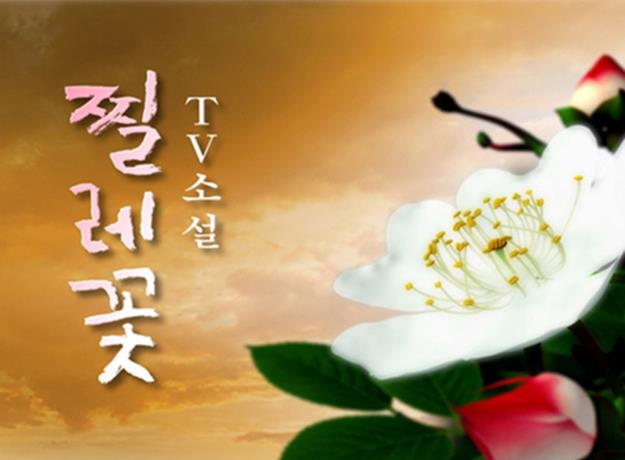
Q2. 지금까지 활동하면서 자신의 대표작 3점을 뽑는다면?
3점만 꼽기에는 조금 아쉽지만, 굳이 뽑아보자면 예전에 아침 프로로 방송된 “생방송 세상의 아침”과 최근의 “영상앨범 산” 타이틀 작업이 좋다는 얘기를 많이 듣습니다. 그리고 다른 하나는 개인적으로 작년에 작업했던 2010상해엑스포 한국관 안에 모니터 198대로 만들어진 멀티미디어타워 캘리그래피 작업입니다. 이 작품은 뛰어났다기 보다는 제가 심혈을 많이 기울인 작업으로 기억에 많이 남네요.
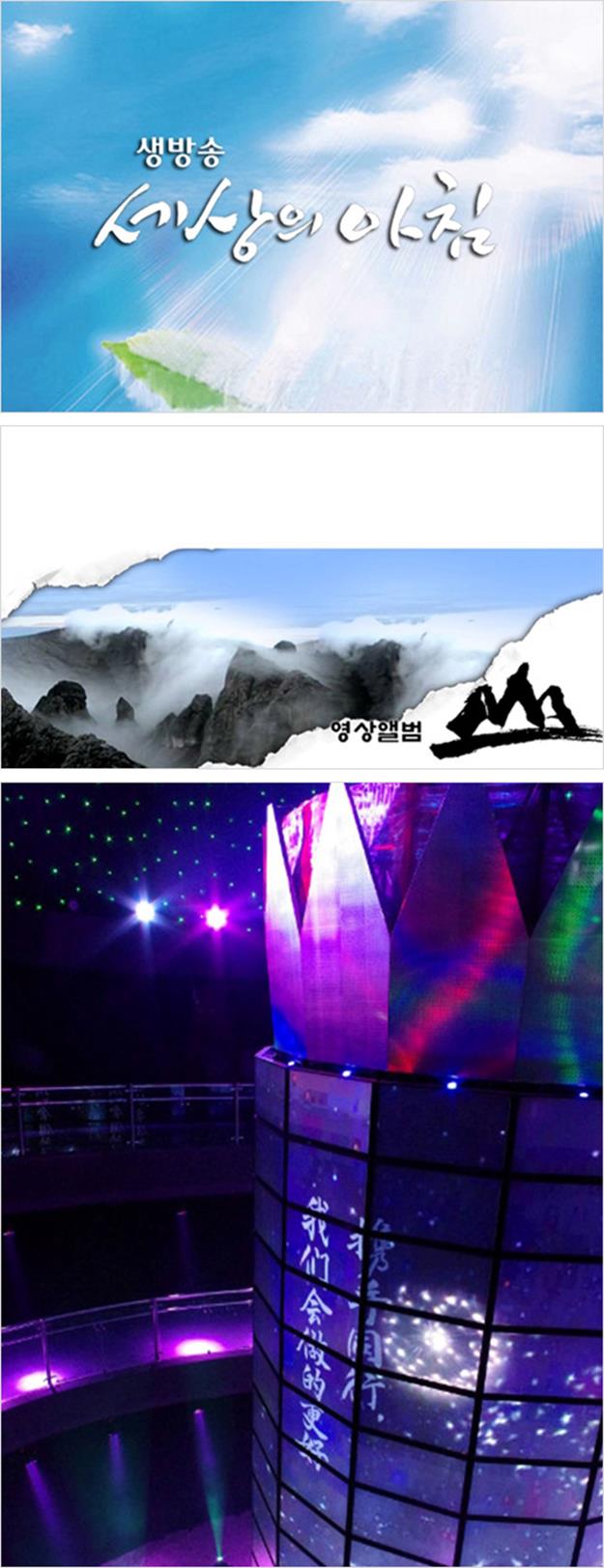
Q3. 일명 B컷이라 불리는 세상에 빛을 보지는 못했지만, 만족스러웠던 작업이 있다면?
방송타이틀을 작업하다 보면 B컷들이 자주 쌓이게 됩니다. 그 중에서 가장 기억에 남으면서 야심 차게 작업했던 게 있는데, 일전에 방영되었던 “불멸의 이순신”입니다. 방송에는 위에 것으로 채택이 되었는데, 제가 심혈을 기울인 것은 아래 쪽이었죠. 아쉬움이 많이 남았던 작업이었습니다.
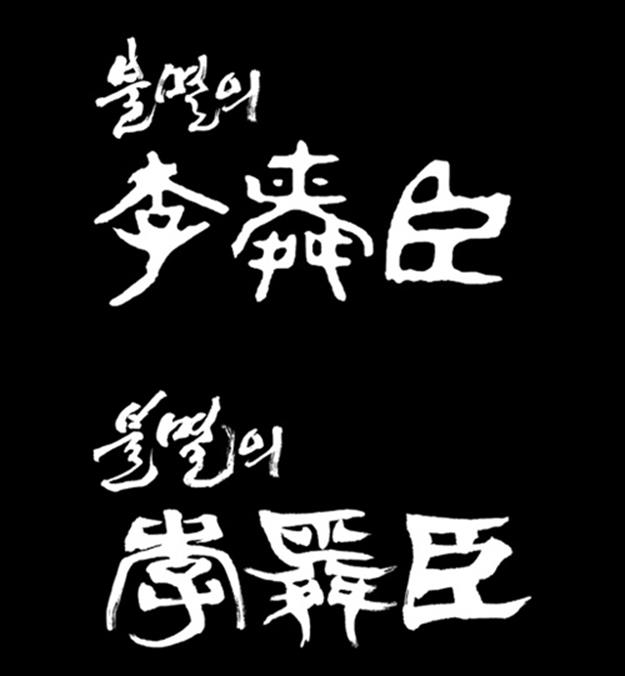
Q4. 캘리그래피에 느끼는 가장 큰 매력은?
캘리그래의 매력은 번짐과 갈필(비백)이라고 생각합니다. 번짐과 비백은 화선지와 붓이 만나야만 만들어낼 수가 있거든요. 이 두 가지 요소가 만나서 가장 한국적인 정서를 담아내는 것 같아요.
Q5. 캘리그래피는 한글과 밀접한 관계를 맺고 있습니다. 캘리그래피 관점에서 한글의 디자인적 매력은?
한글 캘리그래피의 디자인적 매력은 무엇보다 자음과 모음이 만들어내는 앙상블이죠. 자음과 모음의 하모니에 칼라가 들어가고, 다양한 오브제가 첨가되면 현대적으로 색다른 맛을 주게 되는 거죠.
Q6. 캘리그래피 시장이 커질수록 그에 따라 고민해야 할 문제점도 생길 것이라 생각합니다. 현재 캘리그래피 분야에 문제점이 있다면?
요즘 기초가 되어있지 않은 캘리그래퍼들이 너무 많이 늘었다고 생각합니다. 전 늘 아름답지 못한 캘리그래피는 진정한 캘리그래피라고 생각하지 않습니다. 많은 분들이 착각을 하는 부분이 캘리그래피는 바둑처럼 정확히 구분이 되지 않아서 어떤 것이 잘 쓰여진 것이고 어떤 것이 잘못된 작품인지 개개인의 취향에 따라 판단하기도 하는데, 그렇지 않아요.
Q7. CF, 출판, 영화, 방송 등 많은 분야에서 캘리그래피가 각광을 받고 있는데, 이외에도 캘리그래피가 접목될 만한 새로운 분야가 있다면?
앞으론 캘리그래피를 이용한 문화상품개발이 매력이 있다고 봅니다. 이상봉 패션디자이너를 생각해 보시면 충분히 그 의미가 파악될 것 같네요.
Q8. 글씨를 쓰는 데는 붓, 펜, 연필 등 다양한 도구가 사용됩니다. 개인적으로 선호하는 도구는 무엇인가요?
역시 캘리그래피의 매력은 붓이죠. 붓은 굵고 가늘고, 마르고 찰지며, 번짐과 갈필이 다양하게 표현되어 글씨에 감성을 담아내기에 가장 좋은 재료라고 볼 수 있어요.
Q9. 개인적인 취미, 혹은 재충전의 방법은?
개인적으론 주말에 등산과 골프를 즐기는 편이고, 평상시에는 독서를 많이 하는 편입니다.
Q10. 캘리그래피를 배우려는 사람들에게 한마디.
캘리그래피를 잘 쓰려면 새로운 글자체를 만들어내기 보다는 개개인이 어릴 적부터 오랫동안 써 온 펜 글씨의 자형을 붓으로 좀 더 크게 옮기는 작업을 해서 자기만의 서체를 개발하는 게 더 효과적입니다. 어설픈 창작은 오히려 자기 내면의 좋은 악기마저 파손시키는 결과를 초래할 수도 있습니다.
Q11. ‘캘리그래피는 OOO다.’
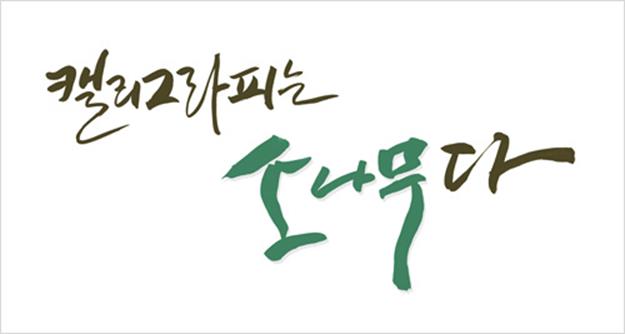
Q1. 캘리그리피 전문가로써 자신의 첫 작품이 궁금합니다.
캘리그래피라는 용어가 보편화되기 훨씬 전부터 서예와 손글씨를 써왔던 저로서는 아쉽지만 첫 작품이 어떤 것이었는지 모호하고 정확하게 보관된 자료가 없습니다. 주로 출판사 북디자이너로 일하며 북 타이틀이 첫 작품일 것으로 생각하는데 아마도 15년 전쯤 소설가 최인호님이 쓰신 수필 <작은 마음의 가슴으로 사랑하라>라는 책의 제목을 쓴 것이 첫 대중적 작품이 아닐까 합니다.
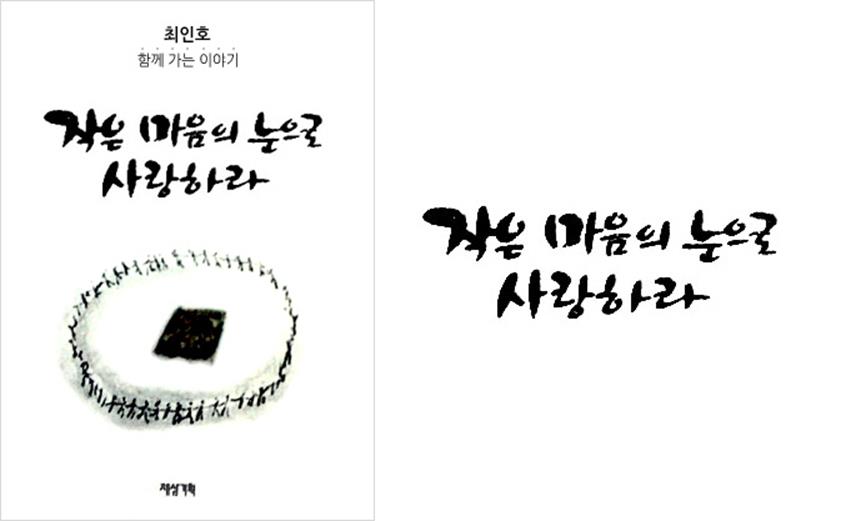
Q2. 지금까지 활동하면서 자신의 대표작 3점을 뽑는다면?
주로 북디자인의 캘리그래피로 웅진 리더스북의 『곡선이 이긴다』, 오마이북의 『 나 같은 늙은이 찾아와줘서 고마워』, 다른우리의 『소비시대의 종교』가 있습니다.
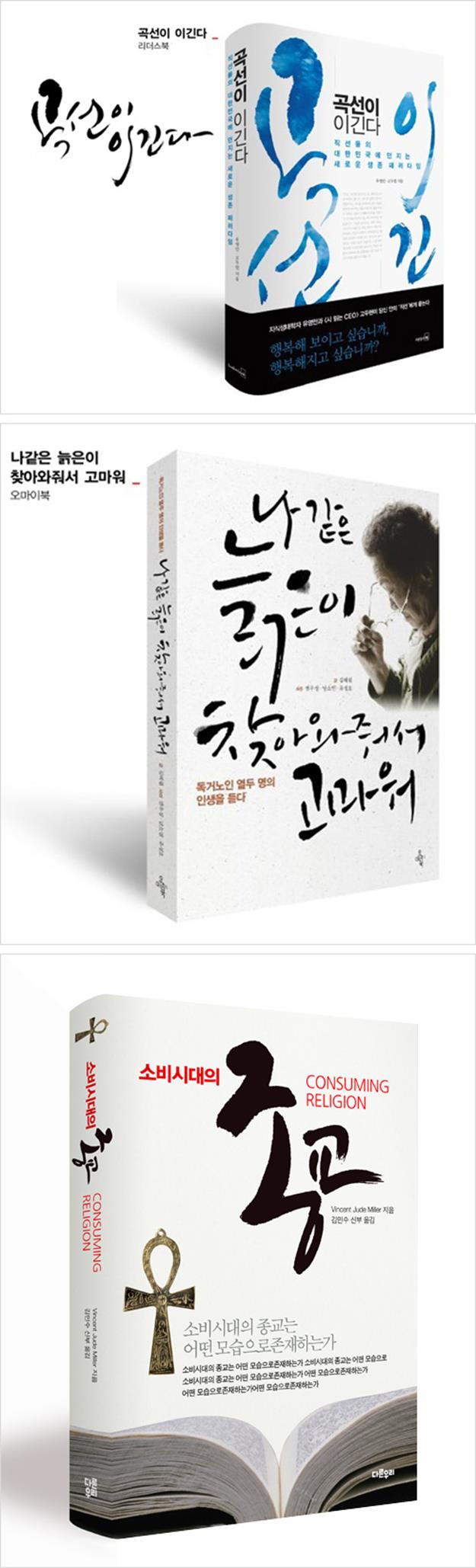
Q3. 일명 B컷이라 불리는 세상에 빛을 보지는 못했지만, 만족스러웠던 작업이 있다면?
캘리그래피는 문장이나 단어가 가지고 있는 의미를 자획에 표현해 내는 작업입니다. 『소통』은 그 의미에 중요성을 『바람부는 언덕에 올라』는 정말 바람이 부는 듯한 느낌을 『7일간의 독서여행』은 자유로운 여행의 느낌을 표현했습니다. 비록 최종적으로 채택되지는 않았지만, 셋 다 좋은 작업이었습니다.
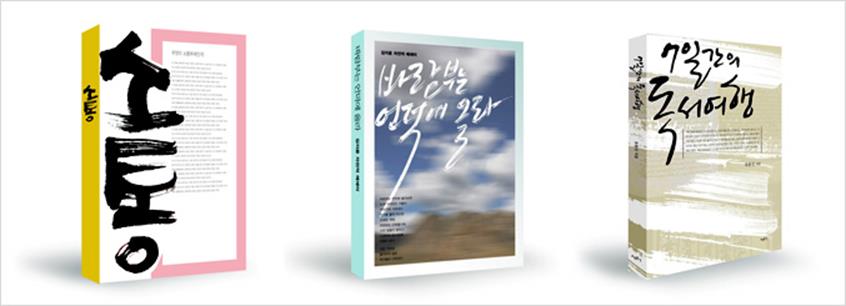
Q4. 캘리그래피에 느끼는 가장 큰 매력은?
어렸을 때 예쁜 만화주인공이나 로봇을 그려봤던 경험은 누구에게나 있을 것입니다. 마치 낙서를 즐기듯 어떤 목적을 두지는 않았지만 그 놀이는 친구가 되고 위로가 되기도 했던 행복한 추억입니다. 캘리그래피는 상업적 목적에 맞게 무엇인가 표현하는 행위이기도 하지만 저에게는 지금도 정서와 마음을 치유해주는 행복한 놀이입니다. 멋진 시구절이나 명언들을 화선지에 옮기면서 느끼는 무제한적 내면의 표현, 이것이 캘리그래피의 매력이라고 생각합니다.
Q5. 캘리그래피는 한글과 밀접한 관계를 맺고 있습니다. 캘리그래피 관점에서 한글의 디자인적 매력은?
대한민국 사람이 한글에 대해 아전인수격으로 설명할 수도 있지만, 디자인적인 면에서 볼 때 영어는 대체로 그 획이 단순하고, 일본어 히라가나의 획일적 간결함은 매우 단조롭고, 한자의 복잡한 획은 표현에 있어 제한적이라고 생각합니다. 이에 비하여 한글은, 예를 들어 그, 리, 이, 기, 으….와 같은 간결한 획과 캘, 풀, 를, 룡, 춤….등의 다소 많은 획을 가진 글자를 두루 가지고 있으며, 이런 글자들의 조합은 다른 어느 나라의 글자보다 멋스러움을 지니고 있습니다. 그렇기에 감성적인 캘리그래피를 표현하기에 매우 훌륭한 글자라고 여겨집니다.(예 : 예술 캘리그래피, 신부님, 고추 좀 따 올랑가?)
Q6. 캘리그래피 시장이 커질수록 그에 따라 고민해야 할 문제점도 생길 것이라 생각합니다. 현재 캘리그래피 분야에 문제점이 있다면?
캘리그래피가 쓰여지는 곳이 넓어지면서 수많은 작가들의 활동도 그만큼 많아졌습니다. 캘리그래피가 한글이 이렇게 아름다울 수 있구나 하는 사회적 인식변화에 엄청난 역할을 한 것은 분명 사실입니다. 캘리그래피가 몇몇 실력 있는 사람들의 전유물인 독점화도 문제가 되지만, 최근에는 시장의 확대와 함께 수준 이하의 작품들로 인해 캘리그래피의 가치를 떨어뜨리는 문제가 발생되고 있습니다. 무제한적 표현의 자유로 인해 오히려 캘리그래피와 아름다운 한글에 부정적 요소를 줄 수 있다는 생각으로 저를 비롯한 작가들은 작품활동에 신중을 다해야만 한다고 생각합니다.
Q7. CF, 출판, 영화, 방송 등 많은 분야에서 캘리그래피가 각광을 받고 있는데, 이외에도 캘리그래피가 접목될 만한 새로운 분야가 있다면?
이미 많은 분야에 빠르게 확산되고 있습니다만 문화분야 외에도 정신의학분야의 치료에 활용한다면 어떨까 하는 생각을 합니다. 저에게 캘리그래피를 공부하는 수강생 한 분이 글씨를 쓰고 나면 마치 오래된 친구와 수다를 떨고 나서 느끼는 기쁨을 느낀다고 합니다. 제 생각에는 캘리그래피의 매력에서 표현한 것처럼 마음의 치유효과가 있다고 봅니다.
글씨를 잘 쓰고 못쓰는 것은 중요하지 않으며 붓을 들고 마음껏 자신의 감정을 표출해 가다 보면 어릴 적 순수한 감정으로 돌아가는 경험을 하게 되는데 그러한 면으로 볼 때 의학분야의 ‘표현 예술 치료’에도 효과적이지 않을까 하는 문외한적인 생각을 해봅니다.
Q8. 글씨를 쓰는 데는 붓, 펜, 연필 등 다양한 도구가 사용됩니다. 개인적으로 선호하는 도구는 무엇인가요?
붓은 어떤 도구보다도 표현의 다양함이 좋아 선호합니다.특히 이미 수명을 다한 붓도 버리지 않는데 오래된 붓은 거칠어지고 뻣뻣해지지만 오히려 그런 도구만이 낼 수 있는 표현이 가능하기 때문입니다. 서예붓 뿐만 아니라 페인트붓이나 화장붓도 활용하곤 합니다.
Q9. 개인적인 취미, 혹은 재충전의 방법은?
음악과 등산을 즐깁니다. 음악은 아마추어 수준이지만 클래식기타 연주하기를 좋아하며 오랫동안 모은 LP와 재즈 CD가 제 작업실의 한 구석에 늘 함께 합니다. 특히 등산은 높은 산이나 유명한 산을 등정하기보다는 특정한 산을 사계절 여러 번 오르내리면서 갈 때마다 자연을 바라보고 변화를 느끼는 것을 좋아합니다.
Q10. 캘리그래피를 배우려는 사람들에게 한마디.
최근 개인강의나 기관을 통해 배출되는 수많은 캘리그래퍼들이 배움을 마치면 바로 붓을 떠나는 경우가 많습니다. 수강을 마치면 금방 무엇인가 써 낼 것 같지만 막상 써보니 그리 쉽지만은 않기 때문이죠.
저는 초등학교 때부터 붓을 벗삼아 글씨를 써왔습니다. 그것이 계기가 되어 지금에 이르렀는데 지금도 출근하면 제일 먼저 먹을 갈고 화선지를 펼쳐서 연습을 위한 무엇인가를 씁니다. 몇 일이라도 붓을 멀리하면 손이 굳고 감각이 둔해짐을 느낍니다. 캘리그래래피는 피아노나 바이올린을 연주하는 것과 같다고 생각합니다. 끊임없는 연습이 있어야 좋은 작품을 낼 수 있습니다.
Q11. ‘캘리그래피는 OOO다.’
캘리작업을 할 때는 작업실에 잘 갖추어진 오디오에 재즈를 넣고 시작합니다. 음악적 리듬과 음율은 캘리작업에 좋은 환경조건으로 음악의 Forte, Pianisimo, Vivace, Andante적인 요소가 캘리그래피와 상통한다고 생각합니다. 캘리그래피 역시 강함과 부드러움, 빠름과 느림에 따라 그 표현력이 다양하기 때문이죠.